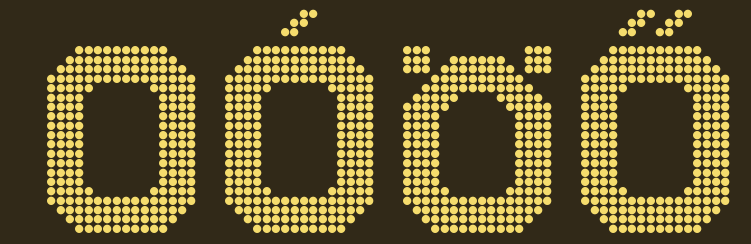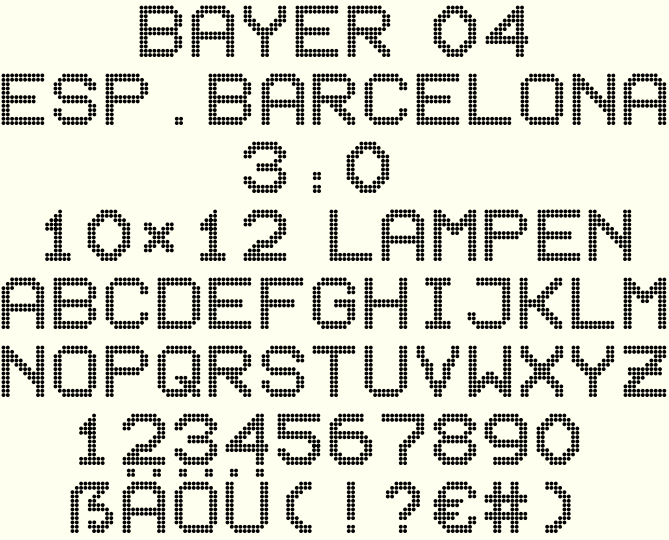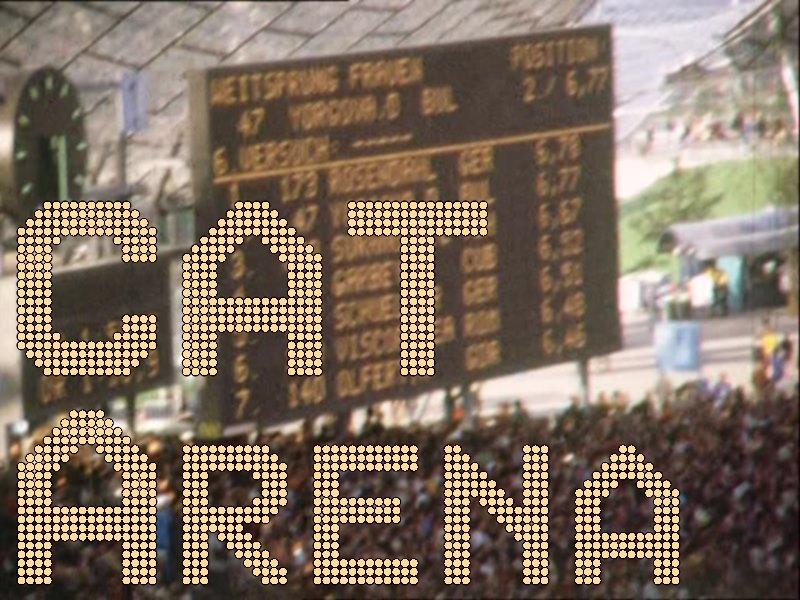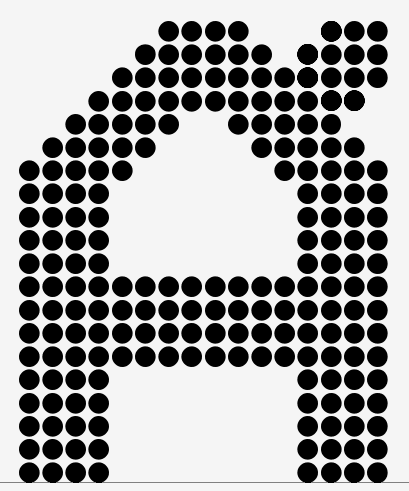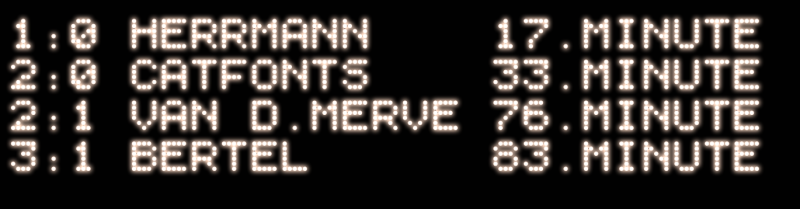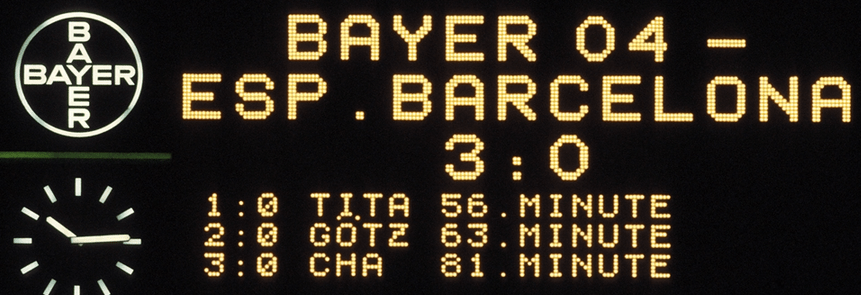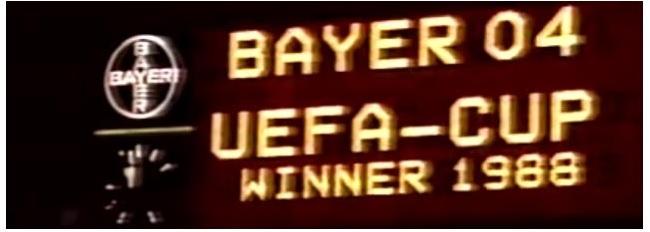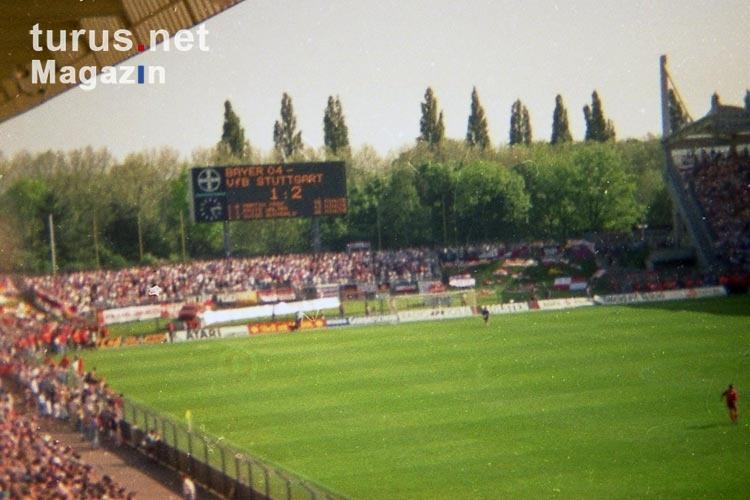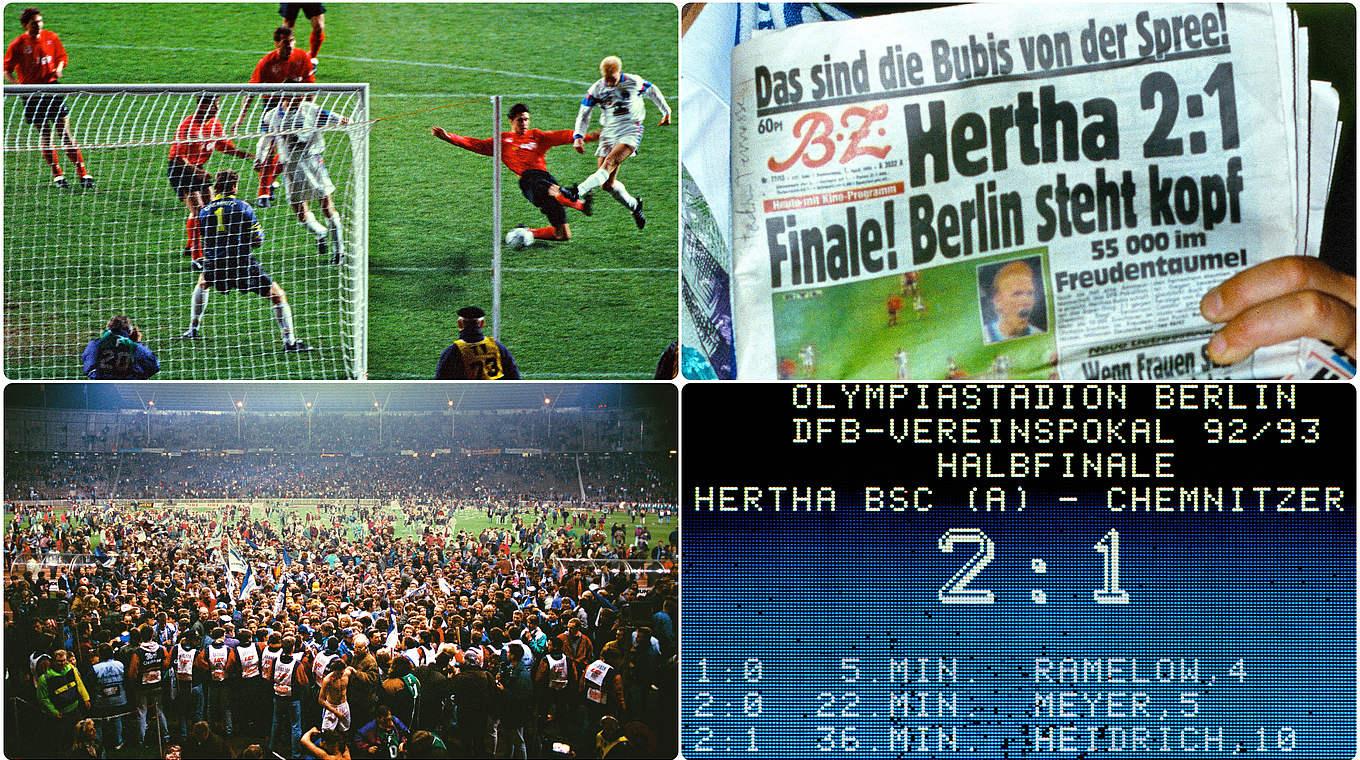
Suche alte Schriftart der Anzeigetafeln aus den Stadien
Hey, ihr seit ja der Hammer. Da bin ich zwei Wochen in Urlaub und die gesuchte Schriftart wurde erstellt - Klasse!
Eine bitte hätte ich noch, könntet ihr die Zahlen auch so nachbauen wie auf dem Bild? 4 geschlossen und etwas breiter zB
Habe noch ein Bild aus dem Netz gefunden von damals....
Oh, das sind jetzt wieder 2 weitere Versionen einer Glühlampenmatrix-Schrift mit niedrigerer Auflösung, als die, welche ich zu erkennen glaubte.
Die obere 12x10 Birnen pro Zeichen, die untere 6 x 5 Birnen
Da muss ich wohl noch mal ran ;-)
Ach herrje! Aber falls du dich sowieso noch mal ran machst, willst du vielleicht auch noch mal die Diakritika unter die Lupe nehmen? Denn so schön die Titelumlaute von Ä, Ö, Ü sind, passen sie halt nicht zu den Akuts. Im Ungarischen stehen die immer nebeneinander, wie in
Und sind die Akuts vielleicht auch ein bisschen zu mager, passten drei Pixel breite besser?
Wobei Ungarn ihre vielen Diakritika ja selbst gern in die Versalhöhe bugsieren. Falls du da nicht weiter friemeln willst, bastele ich mir das vielleicht selbst. Hier ein ganz schnell hingeschubster erster Ansatz für das Á:
und mich jiepert es ein wenig nach
Nur leider habe ich es in Fontlab 5.2 noch nicht hinbekommen,das der Font in Arabisch auch Rechts nach Links funktioniert.
Peter du kanst gedanken lesen. Ich wollte schon nach den arabischen Schriften fragen. :-D
Ja, nur leider habe ich noch immere nicht heraus bekommen, was man Fomzlan 5.2 machen muss, dass die Schrift überhaupt funktioniert.
Ich habe ja schon testweise eine arabische Schrift nur geöffnet, ein Hanza etwas verschoben, und die Schrift wieder genereiert, ohne irgendwas sonst zu ändern, schon funktioniert die Schrift nicht mehr.
Da ja hier die "Birnchen" praktisch konstant weitergehen, sind variable Buchstabenbreiten auch kein Problem Also z.B. eine Staffelung von 0,5 bis 2,5 mal der normalen Buchstaben-Breite.
Aber, wie gesagt ist das eben leider nicht mein Hauptproblem.
Am 2.10.2018 um 01:55 schrieb catfonts:
OK, auch erledigt. Aber polytonisch Griechisch mache ich hier nicht - auch bei noch so viel lieb guck...
na wenn du damit anfangen würdest, käme noch der Wunsch nach einer asiatischen Variante. ;-)
Hallo Jungs, ich hoffe es geht euch allen gut! Ich hätte da wieder eine Bitte 🙂 Es geht um die Zahlen. Ich habe versucht ein paar Beispiele zu sammeln, kann mir einer von euch die Zahlen wie auf der Hertha Anzeige gestalten?! Das 2:1 mit Schatten . Das hatten früher sehr viele.
(die ist sogar aus dem Forum heraus entstanden: spielstand.png
Diese scattiertebn Zuffern hab ich allerdings (noch) nicht.
(hier war es die original Olympia-Anzeigetafel: